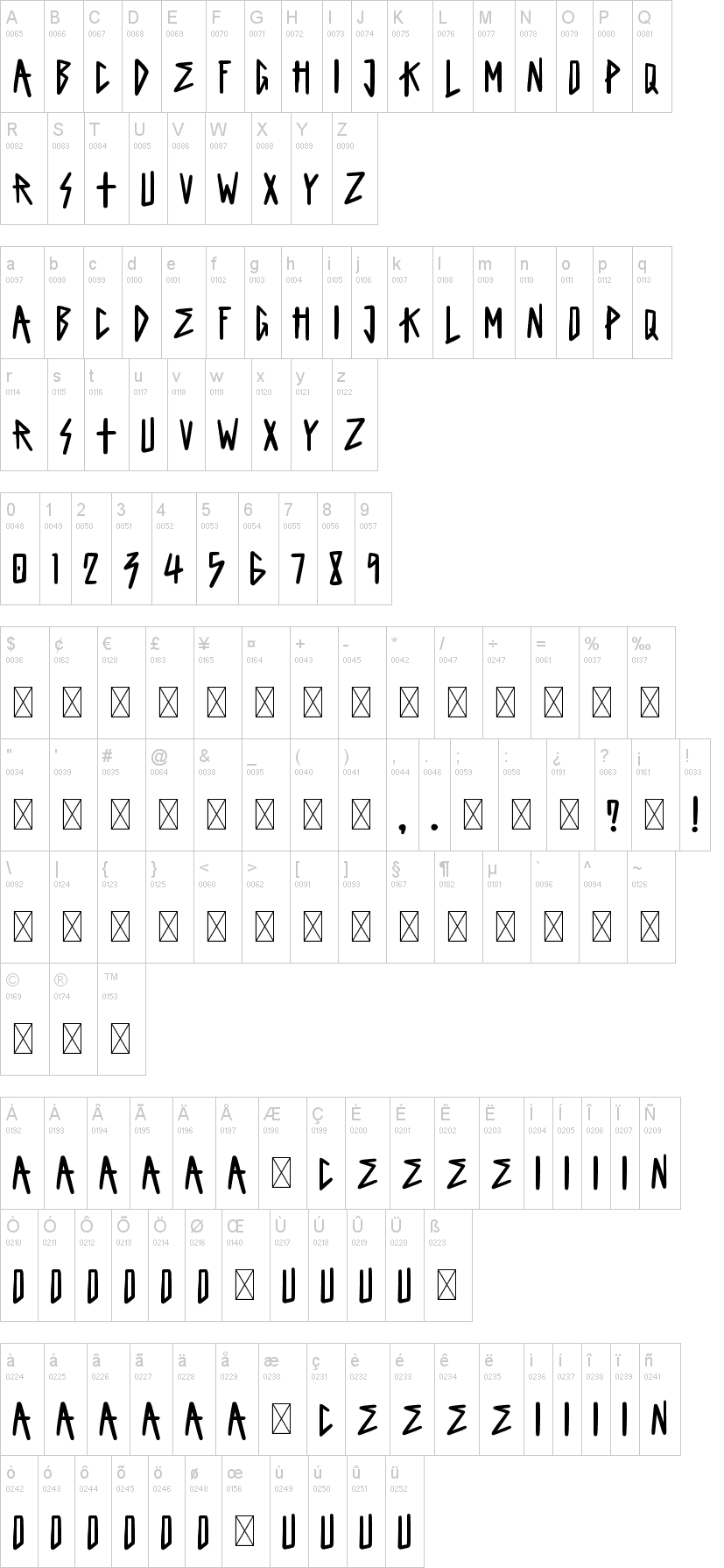
"King of Rock" 是一种字符艺术字体,以其良好的可读性和鲜明的视觉效果而闻名。 这种字体最初由设计师 Jayde Garrow 在 2003 年创建,其中包含了很多独特的设计元素,如加粗的线条和鲜艳的颜色。它的设计灵感来自于摇滚音乐和 20 世纪 50 年代的海报艺术,这使得它在吸引年轻人和音乐爱好者方面非常成功。 King of Rock 字体通常用于音乐海报、音乐类网站、音乐杂志等场合,以及其他需要突出主题和吸引眼球的设计中。它具有强烈的个性和独特的风格,因此是在许多设计项目中广受欢迎的字体之一。内容介绍
King Of Rock是一款非常不错的手写艺术字体,具有很好的视觉感,适合于文化类的宣传设计、商业类品牌的广告和产品包装设计以及个性化文字排版等较多场景。